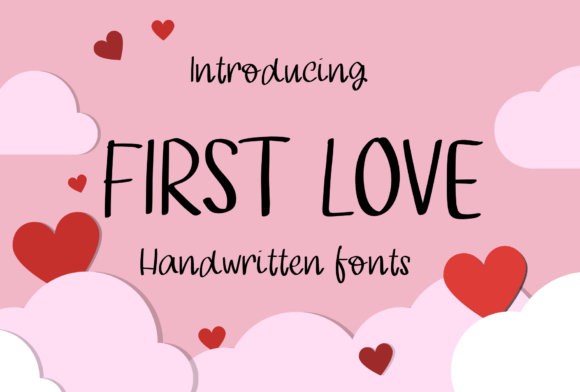
First Love
Conçu avec précision, First Love offre des vecteurs nets, une typographie fluide et une licence commerciale pour une tranquillité d'esprit.